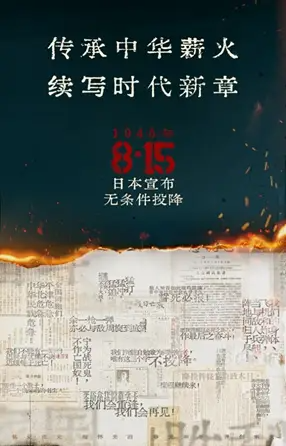
蓝色共鸣推出字体“中华薪火体”
蓝色共鸣在纪念抗战胜利80周年之际,推出字体“中华薪火体”。该字体提取于中国抗日战争时期印刷于报刊、文献中的文字,每个字都是一份力量、一种“铭记历史、缅怀先烈、珍爱和平、开创未来”精神的传承。
遵循近现代印刷品中的字体原型,字形上复刻了棱角分明、端方严谨的特点,为还原历史文献中常见的竖排版方式和油膜缺损的观感,有意进行了高度的压缩和磨损纹理设计。
字体设计师:
王廷瑞、孙正廷、赵博男